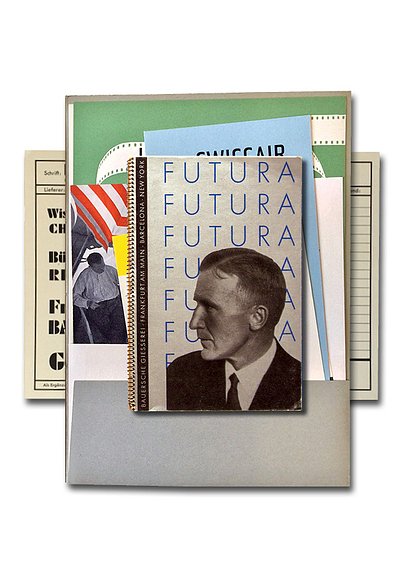
Sonderausstellung im Gutenberg-Museum
Wie eine typische deutsche Schrift, die den Zeitgeist der Avantgarde der zwanziger Jahre fasste, bis heute einen internationalen Siegeszug antreten konnte: Von Frankfurt bis in die Sphären des Kosmos verfolgt die Ausstellung die Entstehung und die Wege der Verbreitung der FUTURA einmal rund um den Globus. Gezeigt werden bedeutsame Originale (Entwurfszeichnungen, Schriftmuster, Drucksachen).
Was war und was ist das Erfolgsgeheimnis dieser Schrift, die bis heute weit verbreitet und bekannt ist?
Um diese Fragen beantworten zu können, konzentriert sich eine neue Sonderausstellung im Mainzer Gutenberg-Museum im Rahmen des Museumsschwerpunkts „Typografie“ und in Kooperation mit der Hochschule Mainz zum einen auf die Entstehungsgeschichte der Schrift. Vorgestellt wird der Entwurfs- und Gestaltungsprozess der einzelnen Buchstaben bis hin zur sukzessiven Publikation der ganzen Schriftfamilie. Anhand designhistorischer Originaldokumente sollen die Motivationen und Entscheidungen, die zu gestalterischen Modifikationen einzelner Buchstaben geführt haben, nachvollziehbar werden. Zum anderen wird die Rezeptionsgeschichte aufgearbeitet. Dabei wird besonders der Frage nachgegangen, warum die Futura in ihrer Zeit so enthusiastisch gefeiert wurde und wie sie sich international durchsetzen konnte.